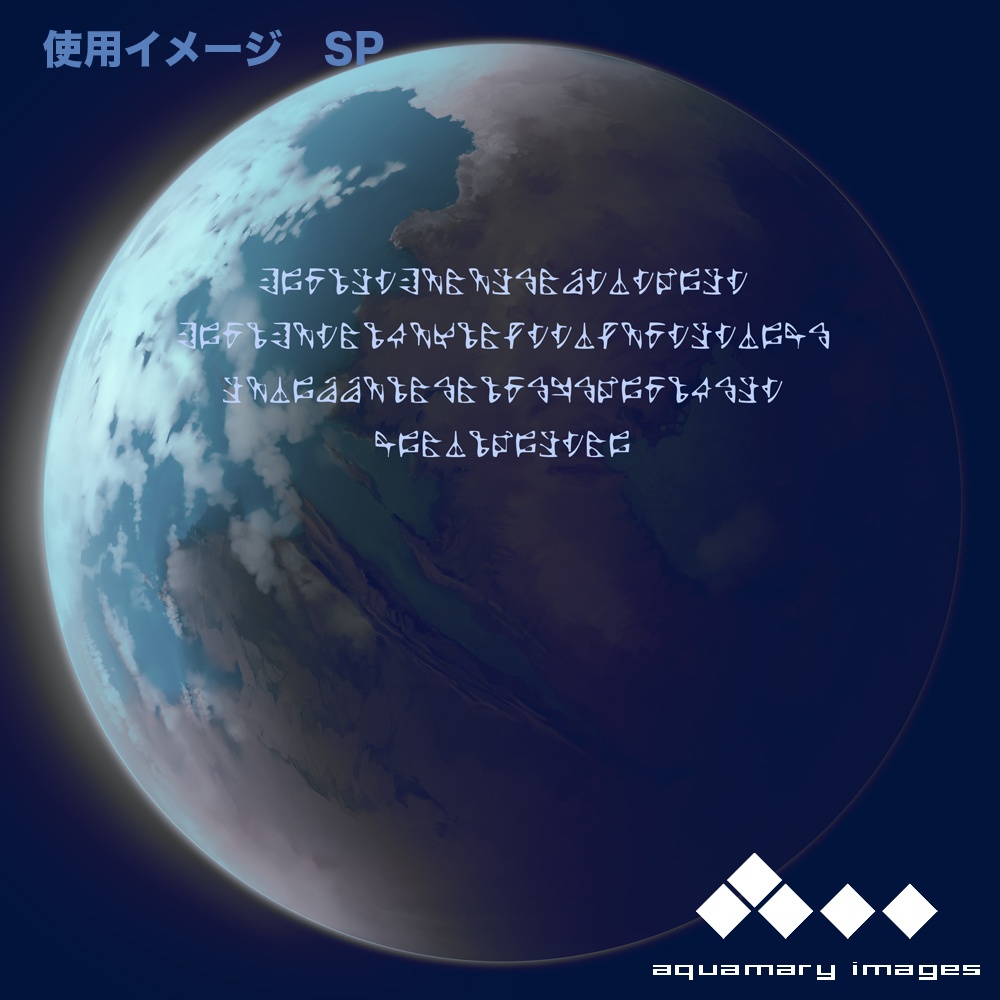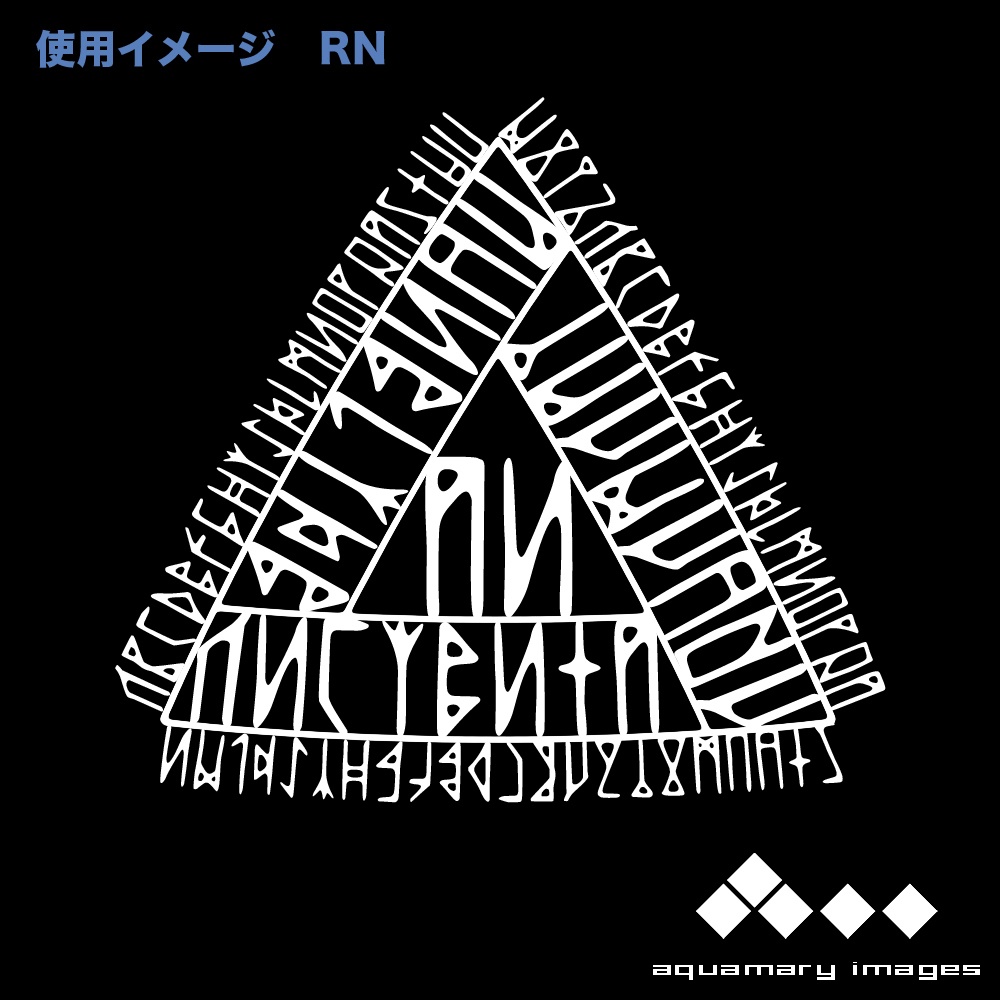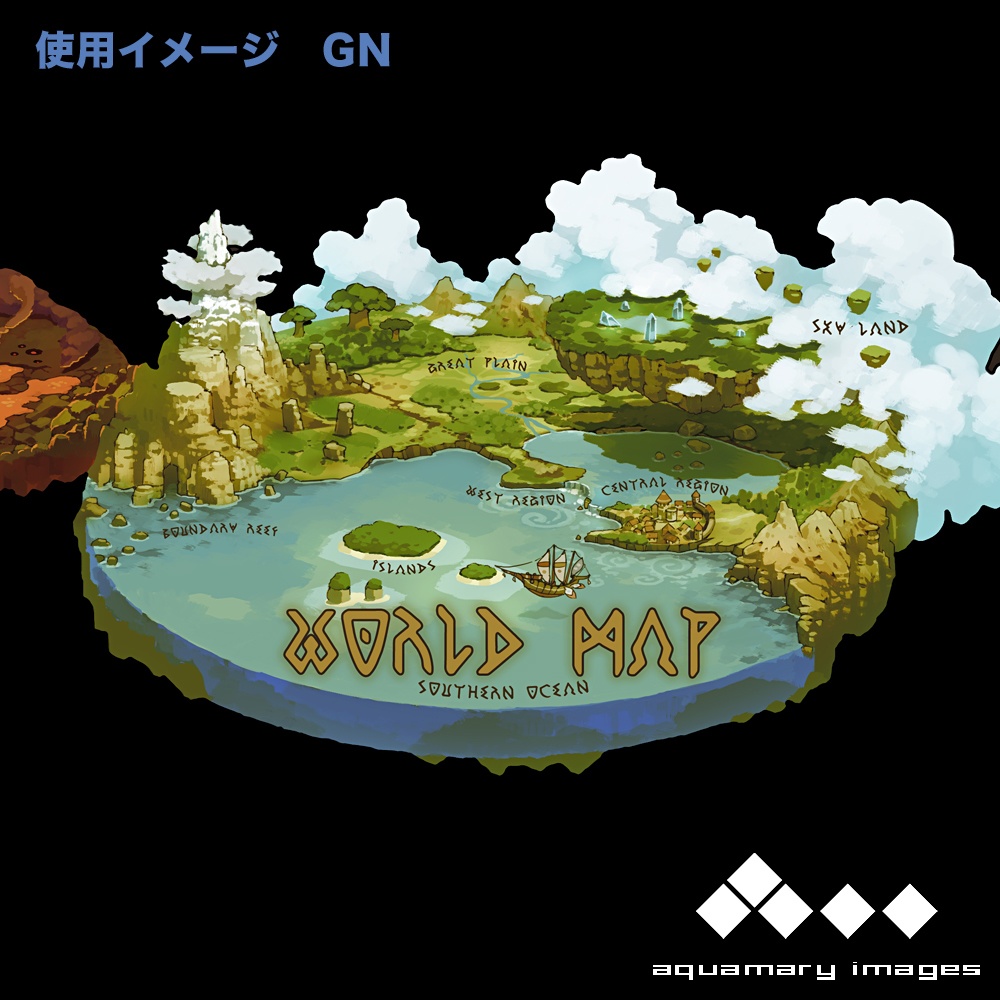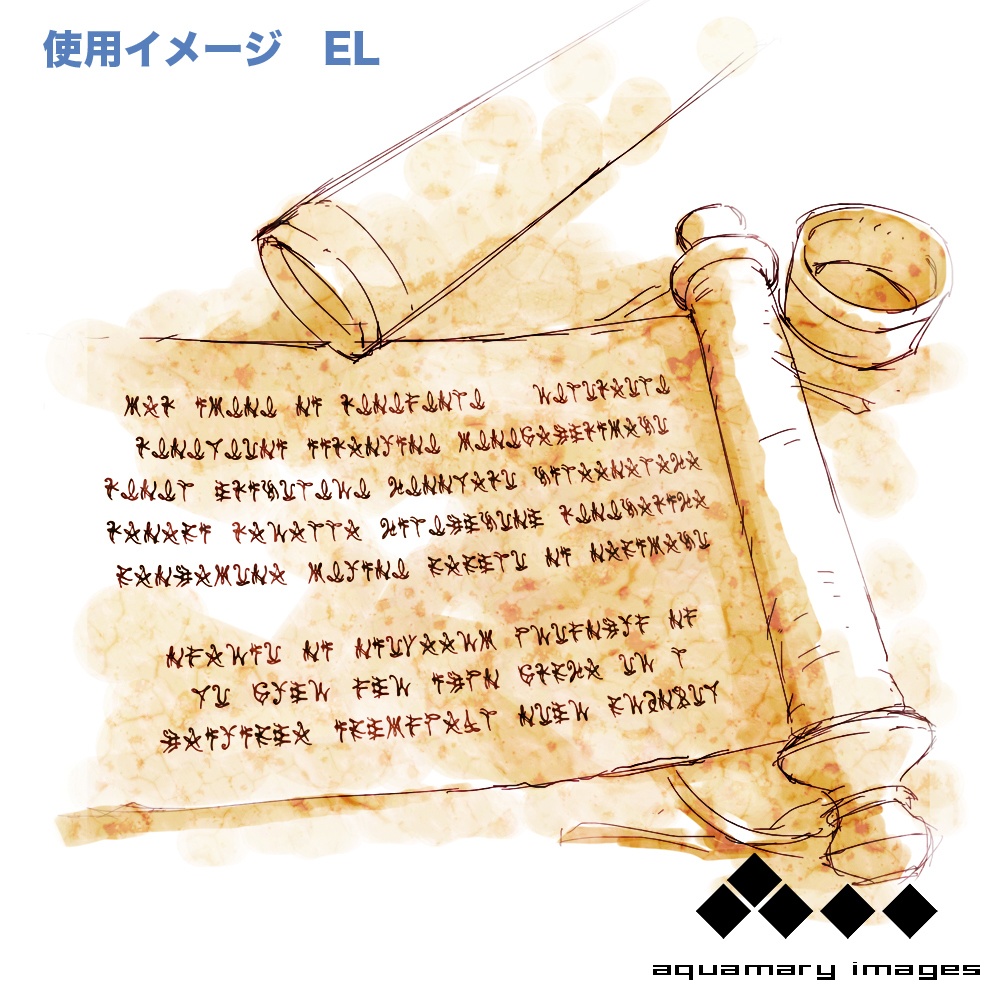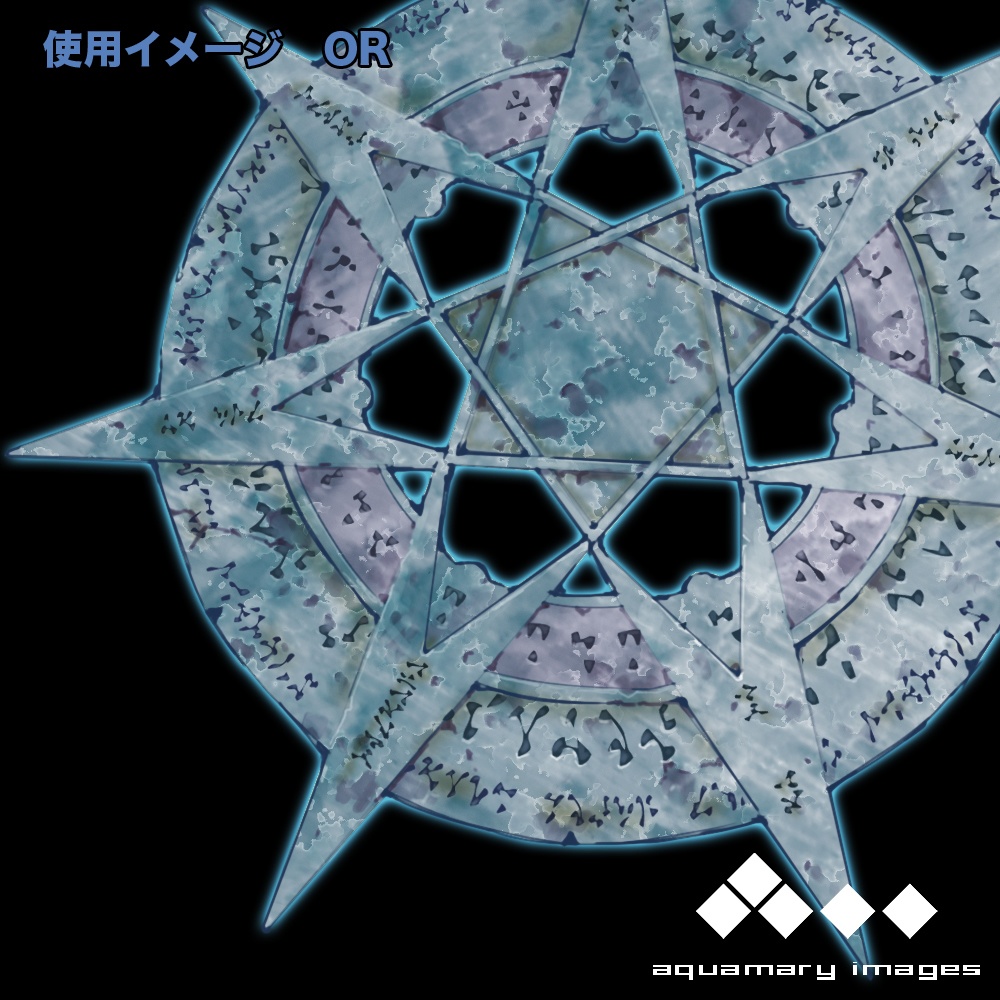
ancientフォント7種セット
架空の文字で一般的な英文字とは異なります。 一部は英文字として「なんとなく読める」ものもあります。 加工することでイラストの装飾素材として使用できます。 Tシャツなどのデザインにもぜひご活用ください。 個人・法人問わず商用利用可(クレジット記載不要) 著作権は放棄していません。 追記:2024年7月20日 [EL]と[OR]の2種を追加して7種セットになりました。
各フォントの収録グリフ
[MG] 大文字・小文字・数字 [SP] 小文字 [RN] 小文字 [GN] 小文字 [SB] 小文字・数字 [EL]小文字・数字 [OR]小文字・数字 記号などは含まれていません。 OpenTypeフォント(.otf)です。